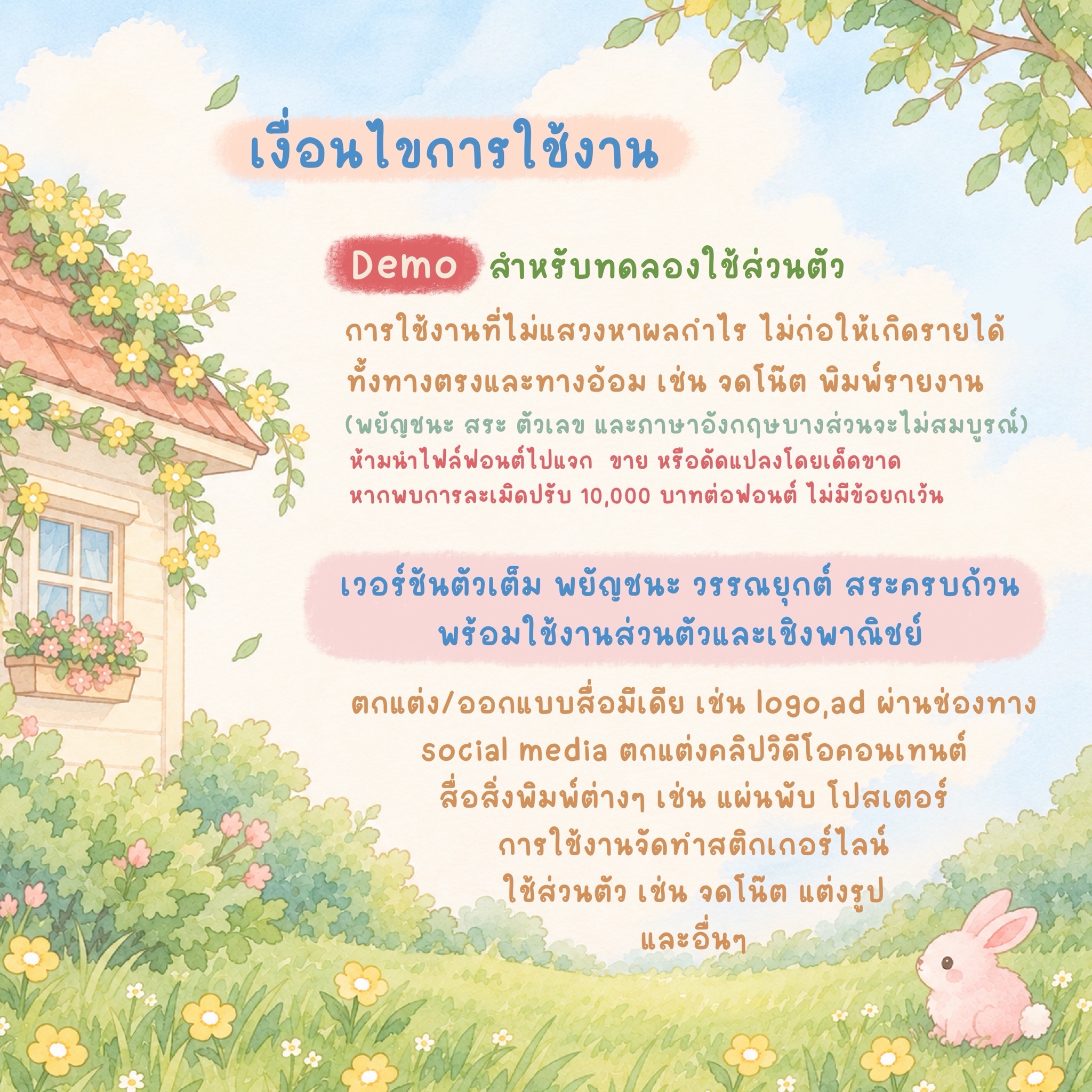
แฟ้มฟอนต์
แฟ้มฟอนต์ชัดเจน (FFChudJen) โหลดฟรีไฟล์ Demo
ชื่อฟอนต์ : ดุสิตสมิต๒๔๖๑
ต้นแบบจากหัวหนังสือพิมพ์ "ดุสิต สมิต" เมื่อปีพ.ศ. ๒๔๖๑ เขียนด้วยอักขรวิธีใหม่สมัย ร.6
พิกัดฟอนต์
พิกัดฟอนต์มือโปร (PKF-muepro)
Wendysfontstore
จองจ้า
ชื่อฟอนต์ : ตะแล๊บแก๊ป๒๔๕๕
"จุด จุด ขีด จุด   ขีด ขีด ขีด   ขีด จุด   ขีด   ขีด ขีด จุด จุด ขีด"  ตะแล๊บแก๊ป..ฟอนต์ที่อ่านไม่ออก แต่ก็อ่านออกอยู่นะ รหัสมอร์สภาษาไทย (คล่องแคล่วแล้วให้กด bold)
Collage House
แจมโรลส์ (PG Jamrolls)
ฟอนต์ลายมือสไตล์น่ารักปุ๊กปิ๊ก อ่านง่าย รองรับ Microsoft, Photoshop, Illustrator, CapCut, ibisPaint, Procreate, Good Note และแอปฯ ต่างๆ ที่มีให้ติดตั้งฟอนต์
SP_KanEng กันเอ็ง
FontHouse
ฟอนต์กู๊ดแลนด์ ( FH GoodLand )
ลายมือสไตล์น่ารักปุ๊กปิ๊กใช้งานได้ทุกโอกาส
เวอร์ชั่นเต็ม มี 3 น้ำหนัก
- ฟอนต์ CkRugby ฟอนต์ลายมือแนวเรียบร้อย เน้นความเป็นระเบียบ อ่านง่ายสบายตาค่ะ